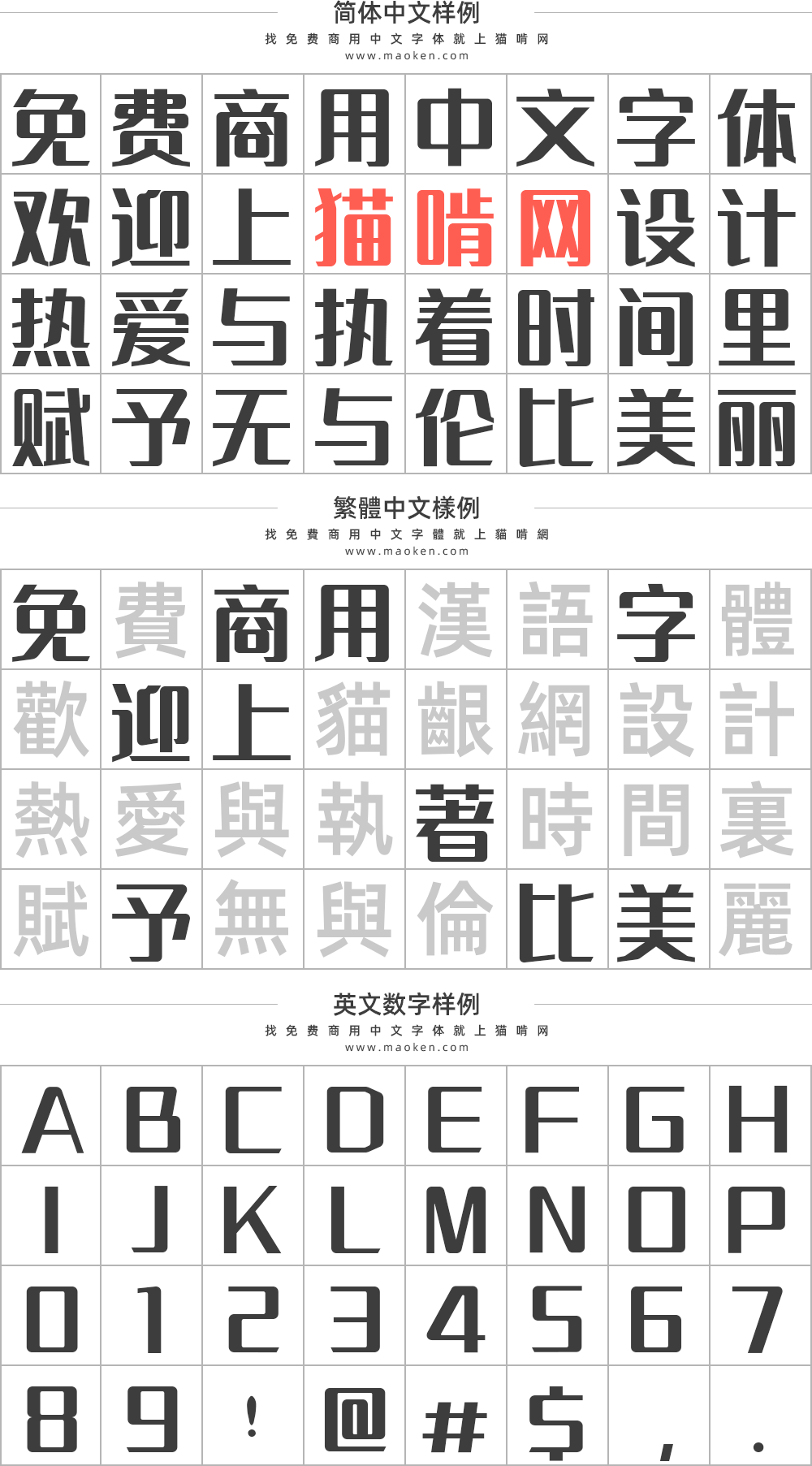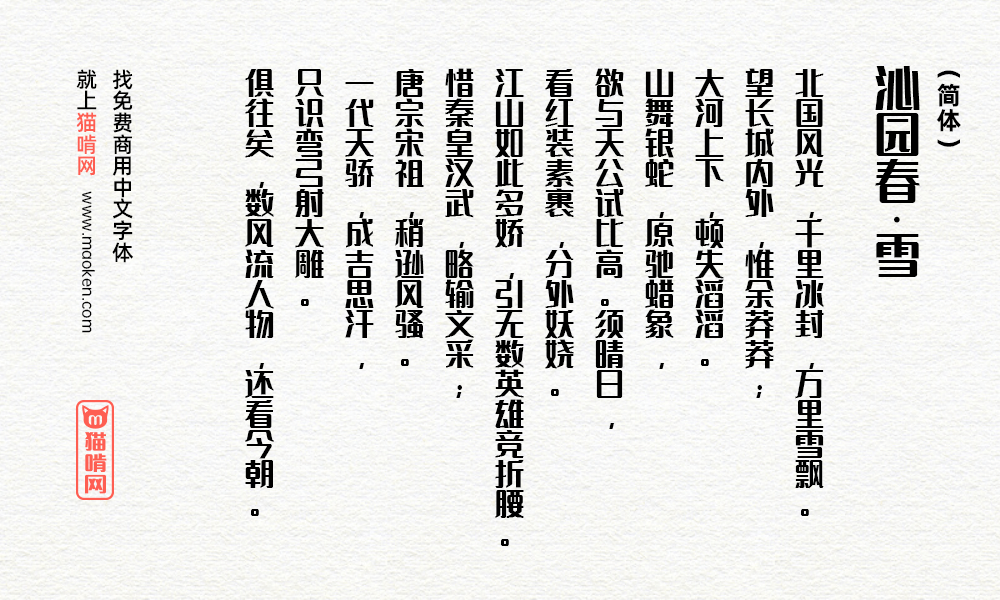
胡晓波男神体:这个胡晓波是真男神 免费商用中文字体
2019年12月23日,在圣诞节前夕,站酷人气设计师胡晓波在庞门正道公众号上一口气发布了三款可免费商用的中文字体。这三款字体分别是胡晓波真帅体、胡晓波骚包体、胡晓波男神体,我们来认真看看这三款字,命名非常骚气,完全符合胡晓波的性格。可以连起来看,一句话说完三个字体:一个骚包的真帅男神。
这三款字体,一共动用了胡晓波工作室7位同事,前后做了1年。人多力量大,就如庞门正道轻松体,80位同学参与,2个月就搞定,但是人少的话,就靠发工资了。这三款字体成本大概在人民币60万左右,所以说啊,所有的好东西,都是钱堆出来。
胡晓波男神体的字形设计阳刚中又带有柔和的转角,横竖笔画对比强烈,提笔走向规律,角度统一,字体边缘整齐,特别适合用于带有刚性的海报设计和标题设计,例如科技、手机、汽车等海报设计。